“见字如面”,一个人写字好看代表的就是他的脸面
随着时间的发展,网络时代已经越来越深入化,电脑、人工智能已经可以替代人工,因此很多人都已经荒废,连走路,写字都不愿意。
尤其是在写字这方面,很多人都已经“提笔忘字”,很多字都已经忘记怎么写了。不但提笔忘字,而且因为太长时间不写字,字写得很丑,就连很多学生也面临这种情况。
但其实字迹好看在考试的时候是很重要的,尤其是在高考的时候,如果你的字迹好看的话,是可以快速的提升成绩。
想一想当老师判卷纸很累的时候,上一秒看到的字迹很丑,下一秒就看到你写得很工整,很漂亮的字,这个时候自然他们就连心情都会变好了,真的是有可能多给你几分。
说到我国公认最好看的字体,相信大家第一时间想到的就是“衡水字体”吧!
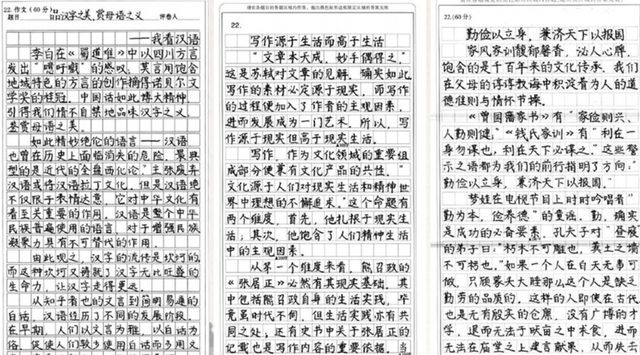
什么是“衡水字体”?
稍微懂一点书法的人都知道“欧体”、“郭体”等,但其实最实用的还是“衡水体”,它总是会在高考的时候被广泛应用。
在书法界可能这种字体并不是很出名,因为它并不属于书法中的一种,也不是太特殊的字体,只是看着比较端正而已,并没有任何的章法。
唯一的关键就是写得“端正”,顾名思义,当初书写这个字体的对象正是衡水中学的高考学生。据悉每年衡水中学在高考的时候,整个班级的语文都会高达55分。
因此“衡水字体”瞬间走红,并且一直流传这么多年,受到高考学生以及老师们的追捧。
衡水字体备受推崇,直到“钱学森字体”曝出后,差距一目了然
但是最近在网上曝出钱学森的一套试卷,引起了网友的关注,因为上面的字体实在是太漂亮了,远远超过了“衡水字体”。
这套试卷出自于20多岁的钱学森之手,当时他就读于交通大学,其实大家不知道的是,钱学森对于文学这方面很感兴趣。儿时的爱好就是看类似于《史记》这种名作。
而网上流传的这套试卷是钱学森的物理试卷,我们可以看到这个物理卷子很难,但是钱学森自然可以考到96分的高分,不愧是学霸。
最令人惊讶的是钱学森不但考出了高分,而且还写出来不同于其他人的字体。
钱学森写得字非常好看,就像“衡水字体”一样工整,但是不同的是,钱学森老先生写得字有自己的灵魂,里面融入了自己的风格。
相比之下,就连备受我国学子和老师推崇的衡水字体都逊色了很多,还是钱学森写得字比较好看。
除了衡水字体和钱学森字体以外,还有哪些字体在高考受欢迎?
书法体
这一类的字体就是我们认知里面接受过专业训练的人写得字,在现在这个时代,学生没有一点特长那是不吃香的。所以很多家长从小就会送孩子去兴趣班。
书法班就是其中一个,学过书法的孩子是可以写出来专业的字体的,因为一般的书法体都是有自己章法的。
只不过想要写出好看的书法体,那么就必须要经过长时间的坚持,只有每天训练,才可以写出来好看的字体。
字迹清晰
对于普通学生来说,是没有得到过书法训练的,其实还是在高考的时候,这一类的学生占比得比较多。
不过有一种最简单的方法,那就是把字写得好看,清晰,这样不但让老师赏心悦目,而且还可以让他们看清楚你写得解题答案。
排版清晰
除了把字写得清楚之外,写字的时候还是会有一些技巧的。比如说写字的大小需要差不多,不要一个大一个小,这样看着也是很不好看的,整体看着会很乱。
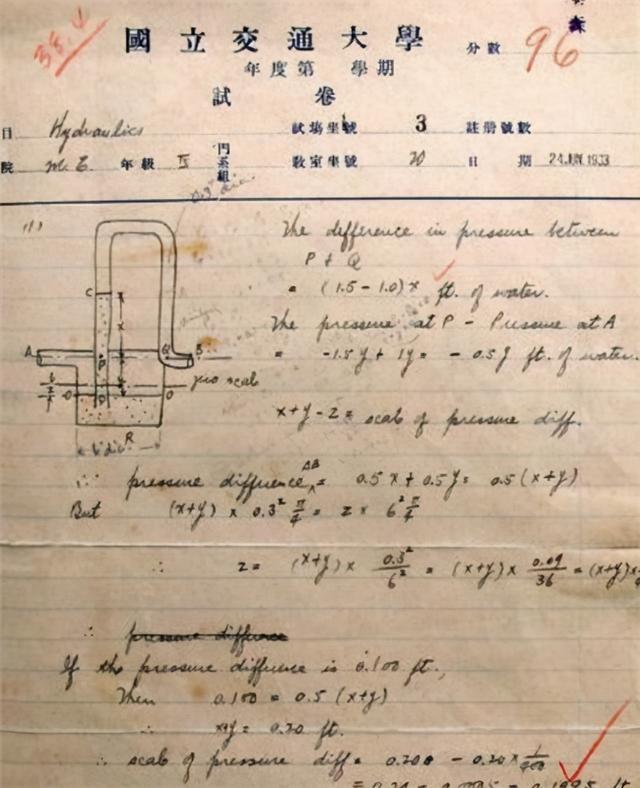
还有字体之间的间距很大,太过于紧凑都是会影响到阅卷老师的心情,最重要的是排版清晰,很多学生在答题的时候,总是把答题卡和试卷都弄得很脏乱差,这样也是会让阅卷老师看着很闹心。